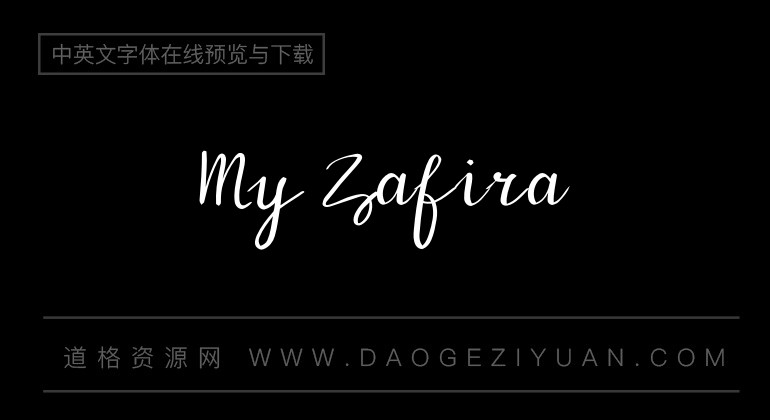
My Zafira 是一款全新的英文字体,由 Fontfabric 公司设计制作。它具有精细的笔画,清晰的结构,流畅的线条,以及柔和的曲线,可以满足各种设计需求。My Zafira 具有很强的可读性,可以用于各种文字和图片的设计,可以让你的文字更加清晰易读。My Zafira 还支持多种字体样式,包括细体、粗体、斜体等,可以根据设计需求进行使用。内容介绍
My Zafira是一款非常不错的手写艺术字体,具有很好的视觉感,适合于文化类的宣传设计、商业类品牌的广告和产品包装设计以及个性化文字排版等较多场景。